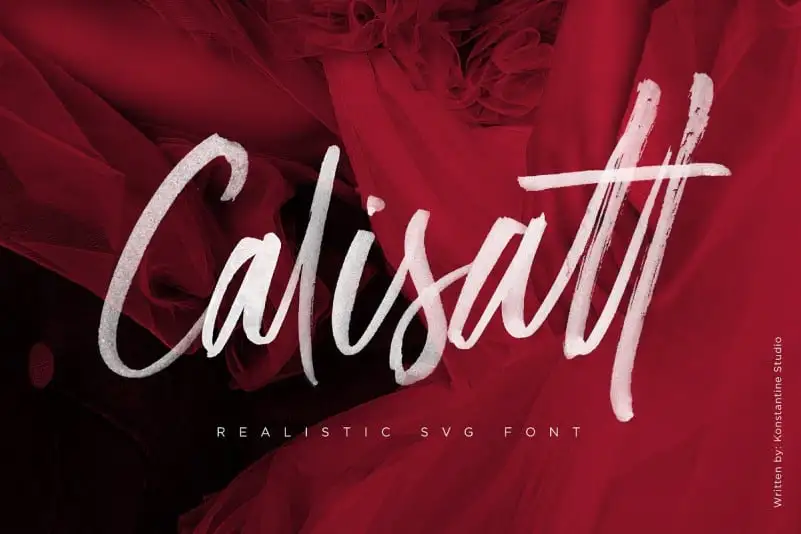
Calisatt Brush SVG Font – Download Grátis
A Calisatt Brush SVG Font é uma nova opção para os designers digitais aventureiros que buscam adicionar detalhes incríveis aos seus projetos de texto e gráficos. Este novo formato, com extensão SVG (Scalable Vector Graphics), permite ao designer incluir mais detalhamento nas letras do que era possível antes. Introduzida pelo Konstantine Studio, esta fonte é uma ferramenta de traço rápido em estilo de tinta e sua versão SVG oferece uma textura única e natural, como se você fosse escrever com suas próprias mãos. Além disso, a Calisatt Brush SVG Font vem embalada com um pacote riquíssimo de ligações que fazem o texto parecer ainda mais vivo e autêntico. É perfeitamente adequado para uso em títulos ou conceitos de exibição, marcas de identidade visual (branding), moodboards conceptuais ou até mesmo na criação de material relacionado à moda e beleza. Com a Calisatt Brush SVG Font, os designers podem explorar sua criatividade com mais liberdade ao criar peças que capturam o espírito jovem e emocionante dos tempos atuais. E melhor ainda, todos esses benefícios estão disponíveis diretamente no formato SVG para um fácil uso em sites web ou aplicativos digitais.